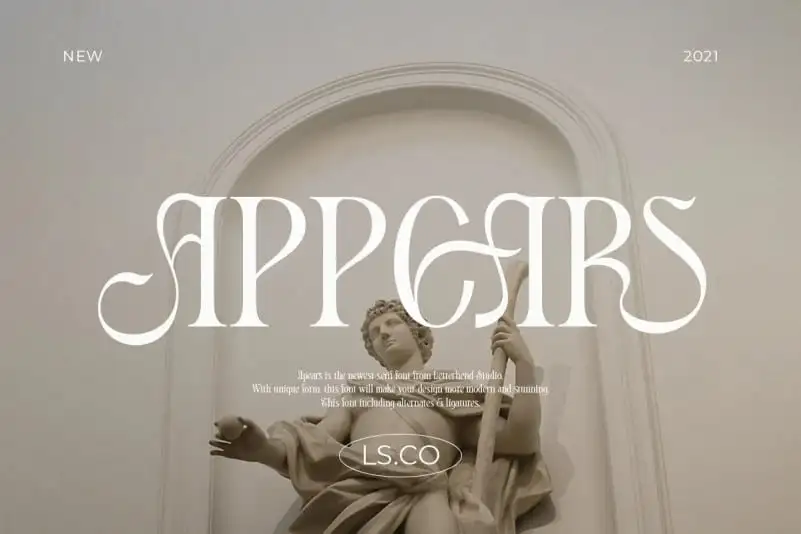
Appears Serif Font – Fonte Grátis
Appears Serif Font
A fonte Serif ‘Appears’ é uma escolha perfeita para projetos que valorizam modernidade elegante junto a uma clássica serif. Fabricada pela Letterhend Studio, esta fonte apresenta linhas definidas e limpas, garantindo um aspecto impressionante para ambientes de design contemporâneo e minimalista. Suas alternativas estilísticas e ligaturas tornam ‘Appears’ ainda mais singular e marcante em meio à multidão. O designer da Letterhend Studio soube capturar a essência sofisticada do estilo serif ao criar um tipo que se encaixa perfeitamente para o design de logotipos, bem como para uma vasta gama de usos formais. Essas incluem convites, rótulos, selos, revistas e livros, cartões de saudação, embalagens, beleza, papelaria, romances, rótulos ou qualquer outra finalidade de propaganda. Apresentando uma combinação excepcional de simplicidade clássica e modernidade, ‘Appears’ é perfeita para quem busca um toque elegante em projetos formais sem perder a essência de sua personalidade. Seja para criar um design minimalista sofisticado ou um logotipo memorável, esta fonte tem o potencial de deixar seu trabalho ainda mais impactante e único no mercado editorial e comercial.